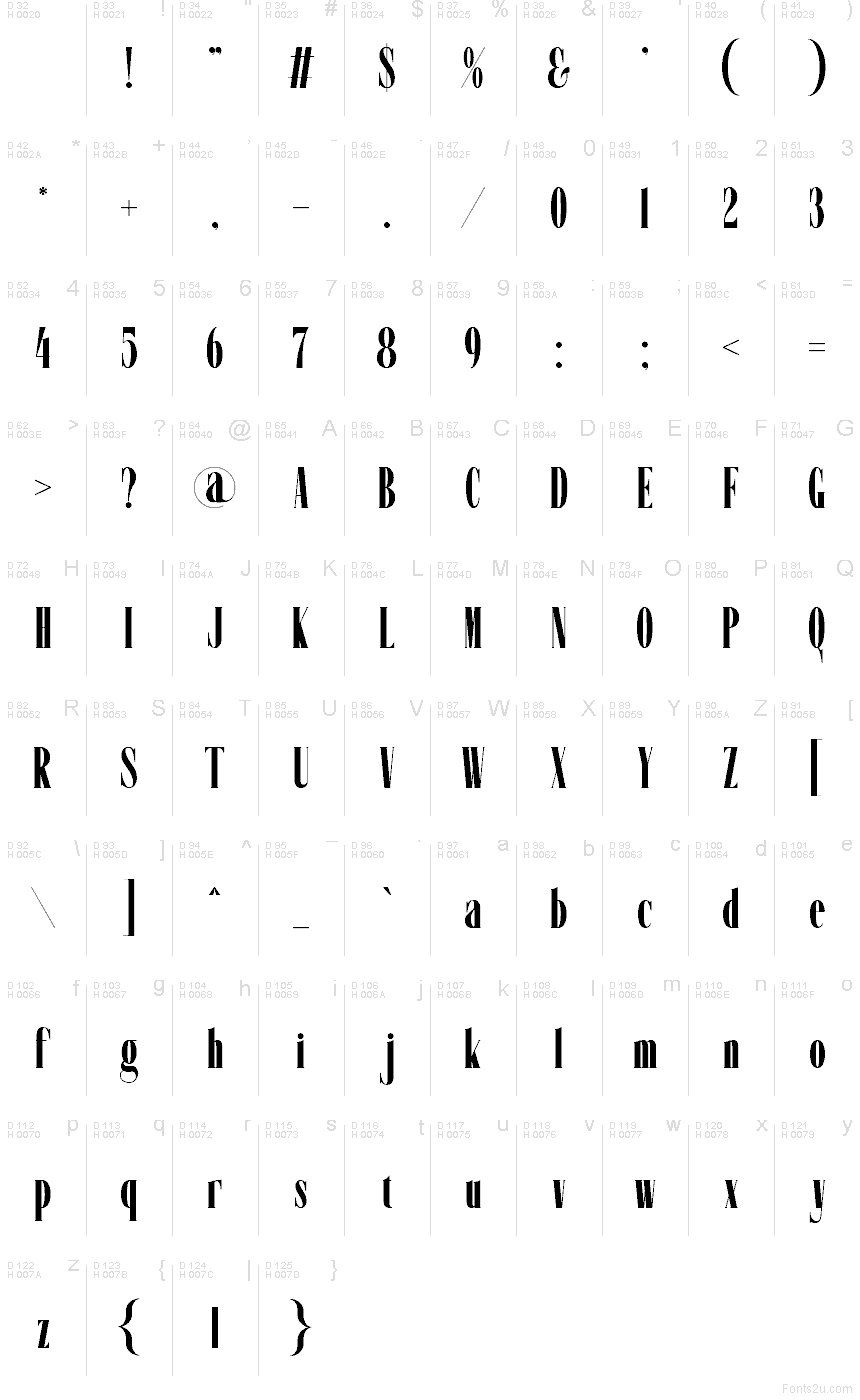
Restiv, da Ermedia Studio, é uma fonte serifada condensada gratuita, com letras excepcionalmente altas e esguias e um forte contraste entre hastes verticais grossas e curvas ultrafinas. Serifas finas e planas enfatizam as proporções condensadas.
As capas de revistas de moda são uma aplicação convincente para esse letreiramento dramático, cuja silhueta alongada mantém sua força visual diante de retratos em primeiro plano e fotografias editoriais de corpo inteiro. Embalagens de perfumes e o branding de boutiques poderiam recorrer à mesma combinação de linhas delicadas e hastes verticais densas para transformar os nomes dos produtos em um elemento reconhecível da marca.